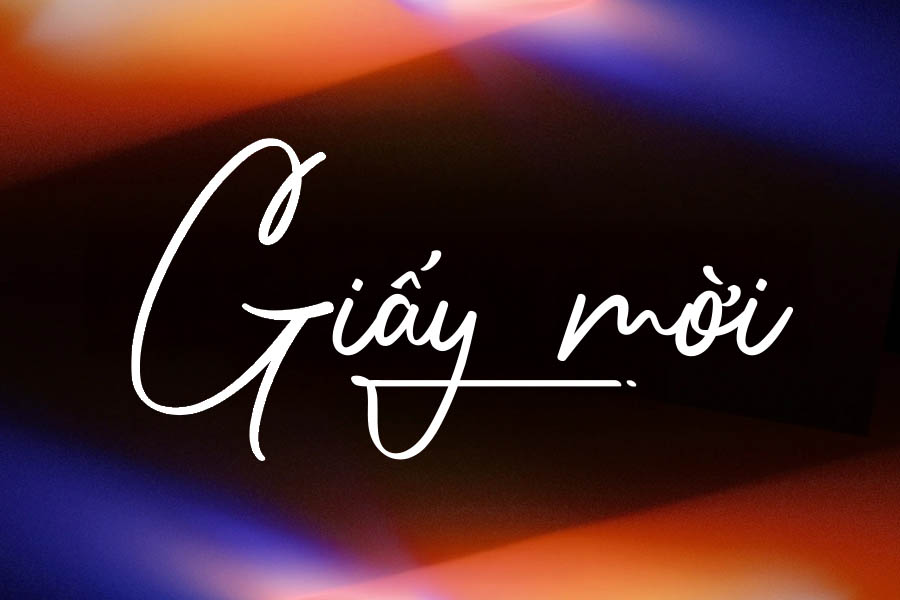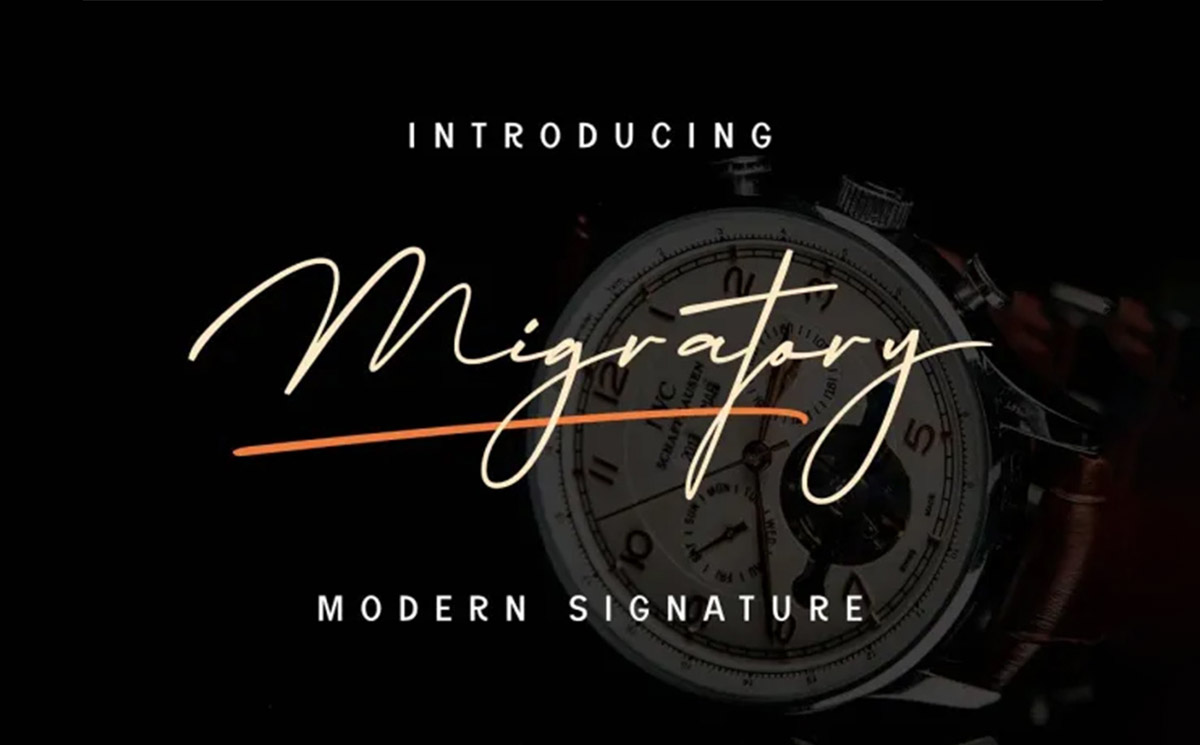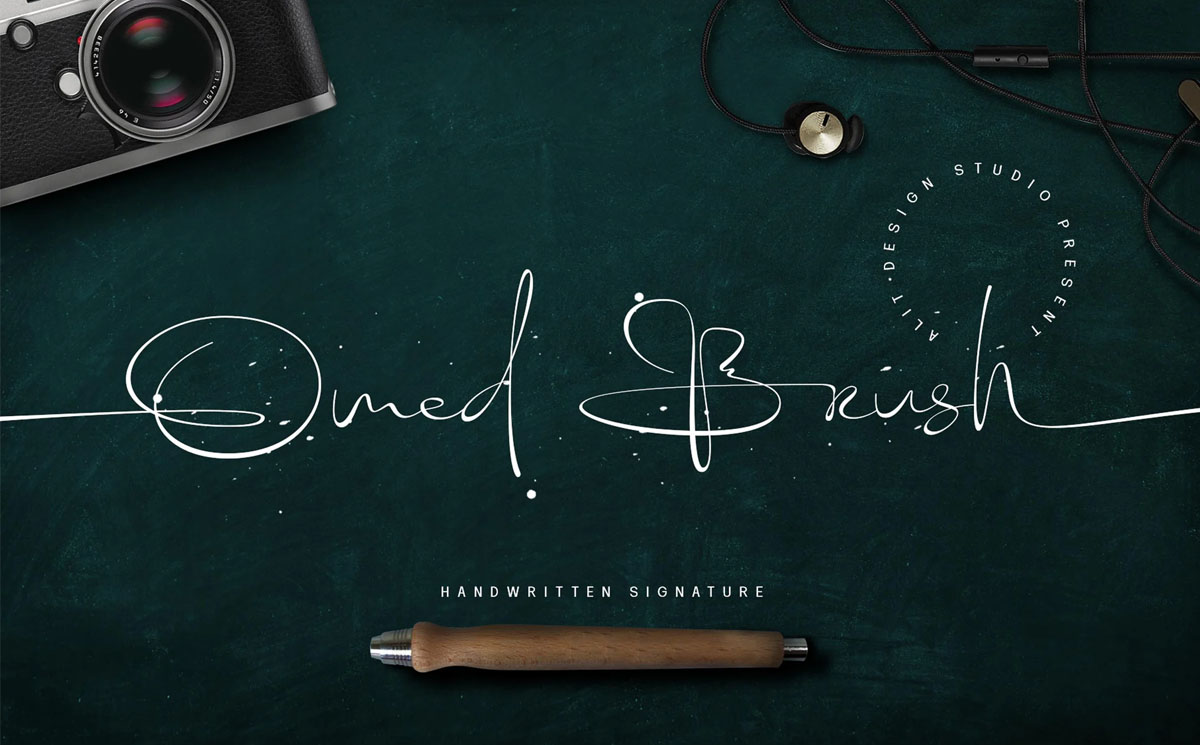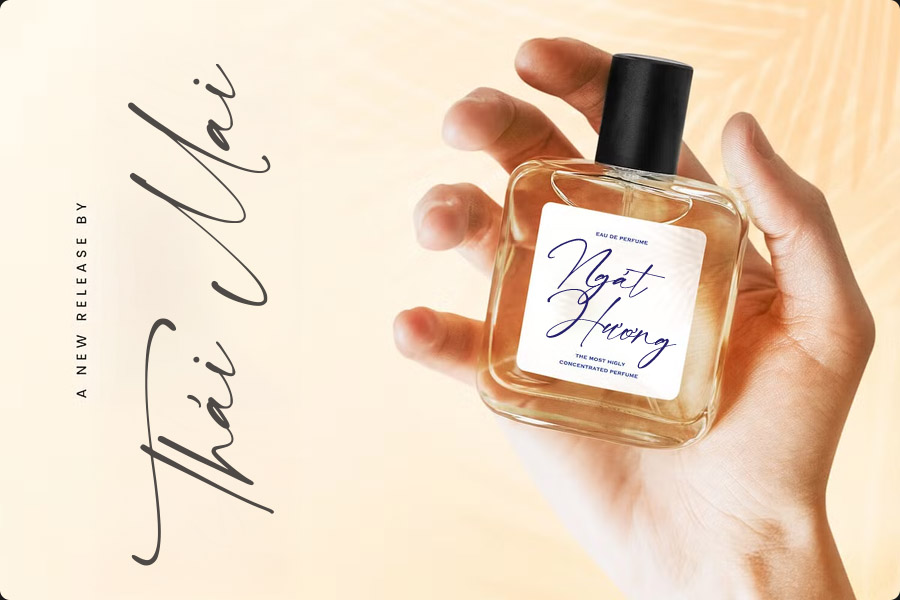
[Tải Về] 12 Font Chữ Ký Việt Hóa Đẹp Nhất 2025 Hỗ Trợ Tiếng Việt
Khám phá 12 font chữ ký Việt hóa đẹp nhất 2025 – dễ dùng, hỗ trợ tiếng Việt, phù hợp CV, logo, watermark và thiết kế cá nhân chuyên nghiệp.
Có bao giờ bạn muốn thêm chữ ký của chính mình vào ảnh hay CV mà lại không biết dùng font nào cho vừa đẹp vừa đúng cá tính? Mình cũng từng loay hoay như vậy khi làm hồ sơ xin việc – viết tay thì không đều, còn font có sẵn thì lại cứng nhắc. Cho đến khi tìm ra những bộ font chữ ký Việt hóa này, mọi thứ như được giải quyết. Từ thiết kế ảnh cá nhân đến watermark cho blog, chỉ cần chọn đúng font là đủ để khiến mọi thứ trông chuyên nghiệp hơn hẳn. Trong bài viết này, mình sẽ chia sẻ những lựa chọn ưng ý nhất năm 2025 – vừa dễ dùng, hỗ trợ tiếng Việt đầy đủ, lại cực kỳ hợp với các thiết kế mang dấu ấn cá nhân.
Font chữ ký là gì?
Font chữ ký (hay còn gọi là signature font) là kiểu chữ mô phỏng nét viết tay tự nhiên của con người, thường được thiết kế để giống như một chữ ký cá nhân. Khác với các kiểu font tiêu chuẩn như serif hay sans-serif, font chữ ký mang tính cá nhân hóa cao, với những đường nét mềm mại, bay bổng, đôi khi nghiêng nhẹ và có liên kết giữa các ký tự.
12 Font Chữ Ký Việt Hóa Được Ưa Thích Nhất 2025
Font chữ TH Mrattoos Regular Việt hóa viết tay nhẹ nhàng
Font chữ TH Mrattoo’s Regular mang kiểu dáng viết tay tự nhiên, với nét chữ mảnh đến trung bình, tạo cảm giác uyển chuyển và duyên dáng. Các ký tự được thiết kế nối liền hoặc đặt gần nhau, mô phỏng cách viết tay liên tục. Đường nét cong mềm mại, không có chân, không tuân theo cấu trúc hình học cứng nhắc mà mang tính tự do và phá cách. Chiều cao các chữ cái thay đổi linh hoạt, tạo nên vẻ sinh động và cá tính. Tổng thể, font này thể hiện rõ chất thủ công và cá nhân hóa, rất phù hợp cho các thiết kế mang phong cách sáng tạo, gần gũi và giàu cảm xúc.
- Tác giả gốc: Alit Suarnegara, thuộc studio nổi tiếng Alit Design.
- Việt hóa bởi: Phạm Sơn - Admin S99, Fontdep.vn
Font chữ ký viết tay SVN Rosellinda Alyamore Việt hóa miễn phí
Font sử dụng nét chữ mảnh, mềm và đều, mang lại cảm giác tinh tế và nhẹ nhàng. Dáng chữ nghiêng phải rõ rệt, thể hiện sự duyên dáng và nữ tính. Các ký tự có đường nét uốn lượn uyển chuyển, được thiết kế theo phong cách viết tay liên tục với phần lớn các chữ nối liền nhau, gợi cảm giác như một chữ ký thanh thoát.
Tỷ lệ chữ cao và thon, đặc biệt là ở các ký tự viết thường, giúp tạo nên vẻ nhẹ nhàng, thanh thoát. Không có chân (sans-serif) và không có yếu tố hình học cứng nhắc, toàn bộ cấu trúc chữ mang tính tự nhiên và giàu tính cá nhân.
- Tác giả gốc: Hanief Farandi thuộc Hanzel Space Studio.
- Việt hóa bởi: STYLEno.1
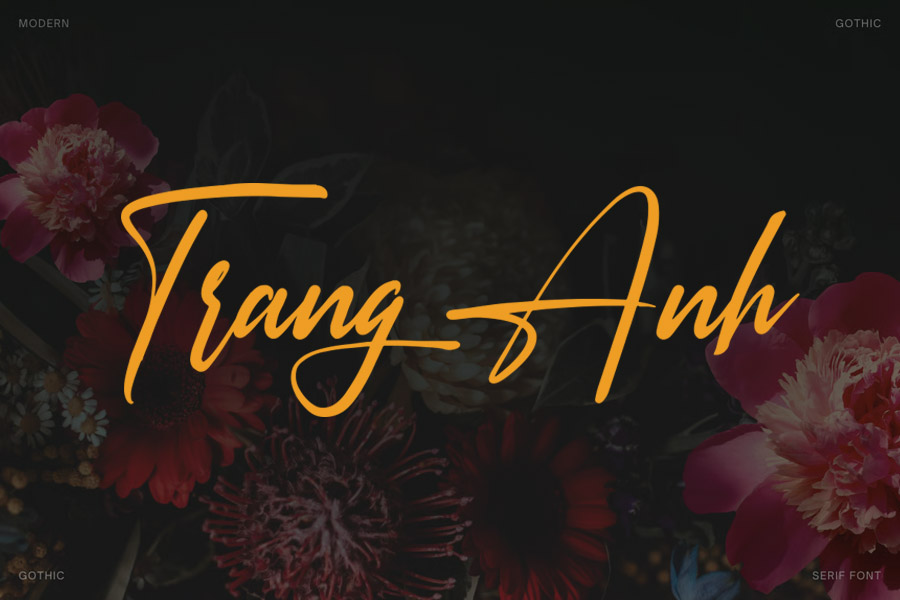
Font chữ TH Bengoda Việt hóa nét mảnh tự nhiên
Font TH Bengoda có kiểu dáng như chữ viết tay mềm mại, mang phong cách chữ ký cá nhân. Nét chữ uốn lượn tự nhiên, liền mạch và thanh thoát, tạo cảm giác nhẹ nhàng, tinh tế nhưng vẫn rõ ràng và dễ đọc. Với đường cong uyển chuyển và liên kết mượt mà giữa các ký tự, font này rất phù hợp cho thiết kế logo cá nhân, thiệp cưới, bìa sách hay các sản phẩm cần sự sang trọng và cảm xúc.
- Tác giả gốc: Yudi Pratama Chandra – nhà sáng lập Rantautype Studio.
- Việt hóa bởi: Phạm Sơn - Admin S99, Fontdep.vn
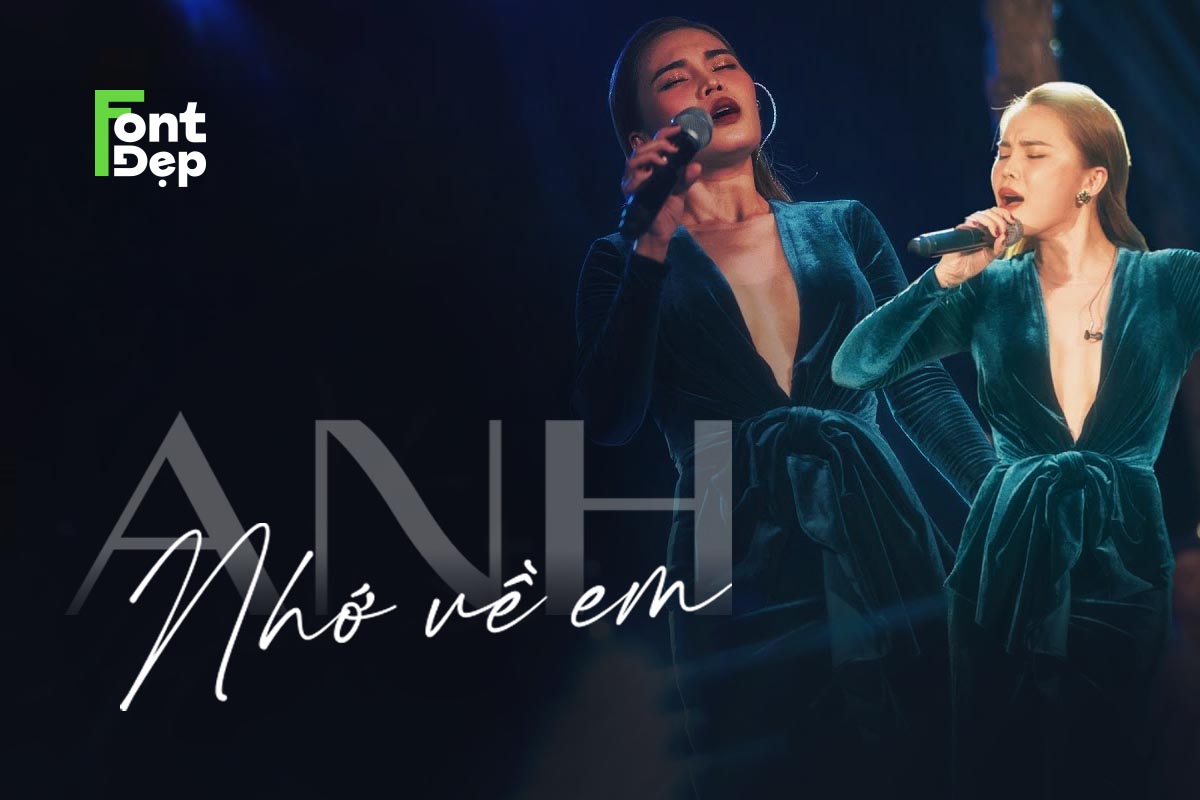
Font chữ TH Jalliya – 7 kiểu chữ ký trong 1 bộ font
Font TH Jalliya mang phong cách chữ ký viết tay mềm mại và tự nhiên, với các nét chữ uốn lượn thanh thoát, tạo cảm giác như được viết bằng bút mực thật. Kiểu dáng này mang lại vẻ gần gũi, tinh tế và đầy cảm xúc, rất phù hợp cho các thiết kế mang tính cá nhân hóa như thiệp cưới, logo thương hiệu cá nhân, bìa sách hay bao bì sản phẩm. Font cũng hỗ trợ đầy đủ tiếng Việt, giúp hiển thị mượt mà và thẩm mỹ trong mọi ứng dụng.
- Tác giả gốc: Achmad Hanif Ulinuha, người sáng lập Madhaline Studio
- Việt hóa bởi: Phạm Sơn - Admin S99, Fontdep.vn
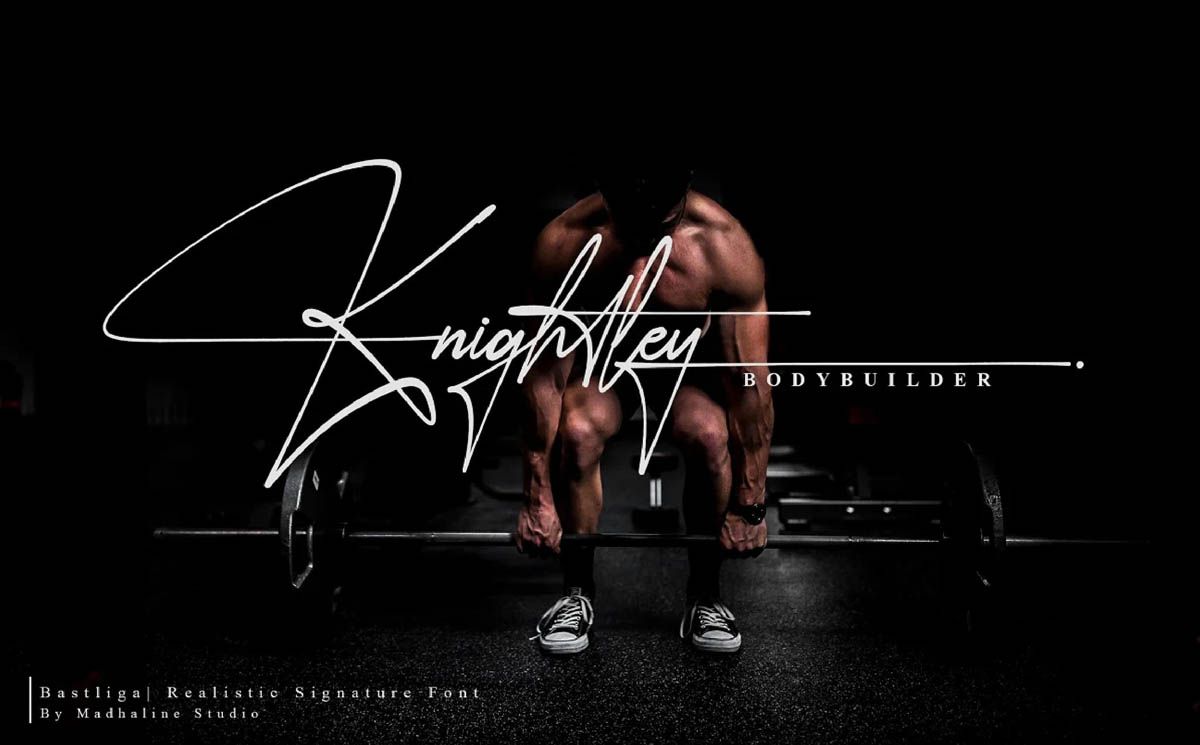
Font chữ TH Milyah – Hiện đại, rõ nét, chuyên nghiệp
Font này là sự kết hợp của các nét cong phức tạp, gạch nối dài và dấu xoáy kiểu vẽ tay cầu kỳ. Nhìn qua có thể thấy hơi rối, nhưng thực tế lại mang đến cảm giác “signature real” – như một chữ ký thật của người nổi tiếng. Rất hợp để làm logo cá nhân cao cấp hoặc branding sang trọng, riêng biệt.
- Tác giả gốc: Nurf Designs – một studio thiết kế font đến từ Indonesia
- Việt hóa bởi: Phạm Sơn - Admin S99, Fontdep.vn
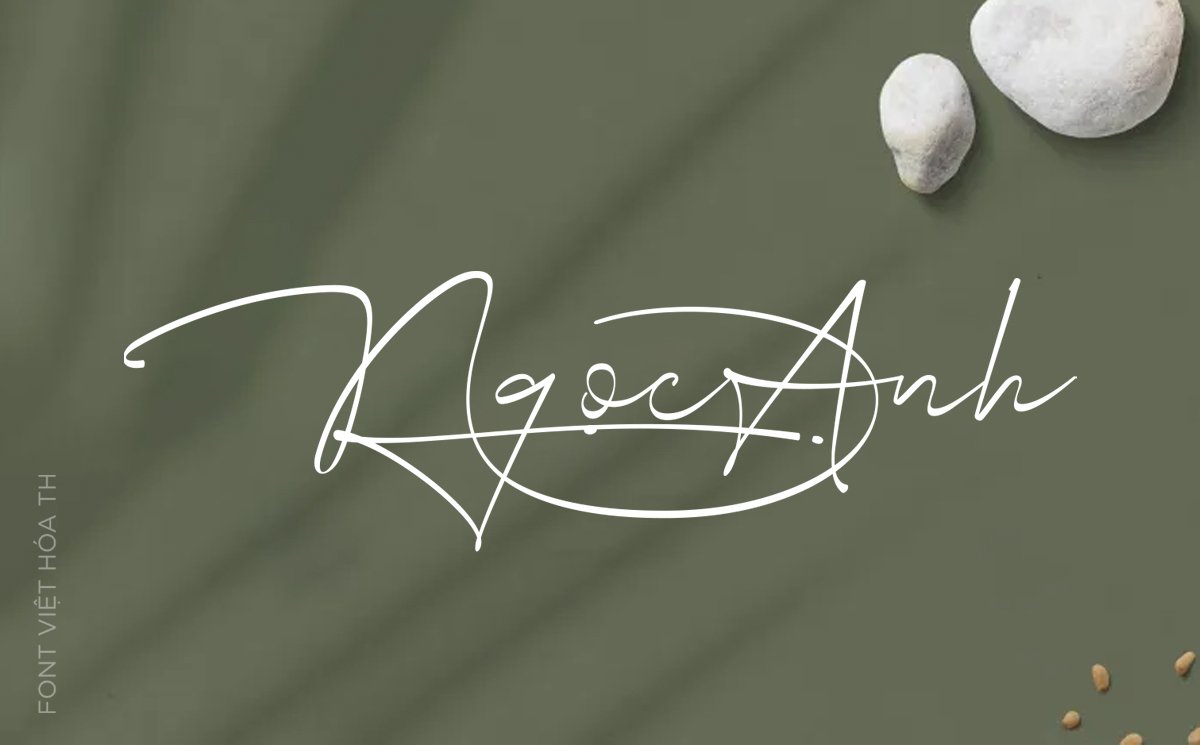
Font chữ TH Maistoray – Cổ điển, mang chút hoài niệm
Nếu bạn yêu cảm giác viết thư tay, TH Maistoray chắc chắn sẽ làm bạn thấy thân quen. Font mang hơi hướng cổ điển, với các đường uốn lượn vừa phải, nét nghiêng tự nhiên và cấu trúc chữ thoáng. Rất thích hợp với các thiết kế in vintage, thiệp viết tay, bưu thiếp hoặc chữ ký thương hiệu mang tính truyền thống. Phiên bản Việt hóa đầy đủ hỗ trợ tốt khi dùng tiếng Việt.
- Tác giả gốc: Par Nu
- Việt hóa bởi: Phạm Sơn - Admin S99, Fontdep.vn
Chọn một font chữ ký phù hợp không chỉ là chuyện thẩm mỹ – nó còn là cách bạn nói lên phong cách, cảm xúc và dấu ấn cá nhân qua từng dòng chữ. Dù bạn là designer, freelancer hay chỉ đơn giản là người yêu cái đẹp trong từng chi tiết nhỏ, thì những bộ font Việt hóa trong danh sách trên chắc chắn sẽ mang đến cho bạn nhiều cảm hứng. Hãy thử vài kiểu font, đặt tên mình vào, và xem điều kỳ diệu xảy ra nhé.